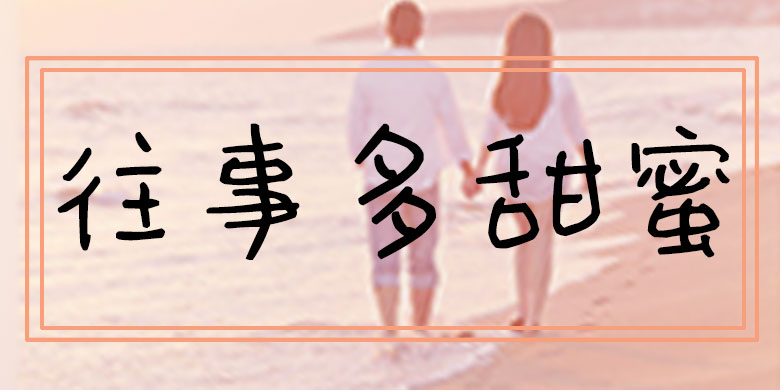
品牌:方正手迹设计师:余丹发行时间:2019字库编码:大陆简体(GB2312-80)分类:创意书写字体属性:精品字
字形可爱,笔画夸张,采用变形手法,参差并极具张力。线条简洁,转折圆滑,简洁流畅,单纯可爱。笔画的跃动感极强,给字体带来了生命力,显得朝气蓬勃,可爱动人。适用于少年儿童类的书刊、品牌广告和产品包装设计,以及社交网络的个性化用字。